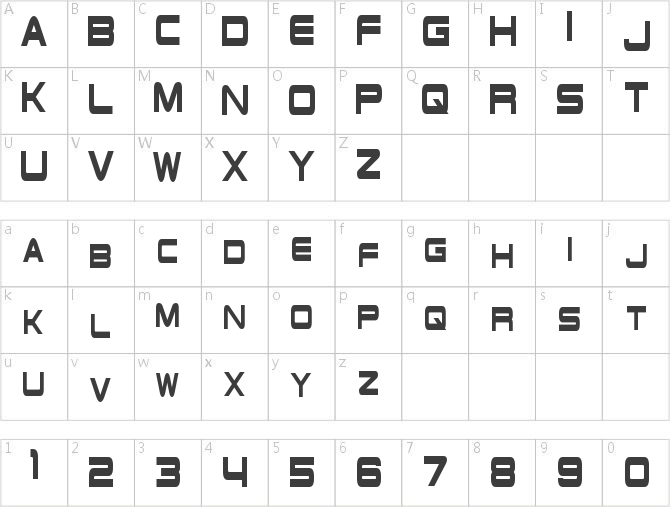
Schwarzenegger Condensed
Schwarzenegger Condensed介绍
Schwarzenegger Condensed字体字库是一款让人赏心悦目、百看不厌的英文字体,适合各类广告和产品包装设计应用,字体大小0.09MB,格式为ttf字体,上传用户是多喝烫水,作者/版权方为未知